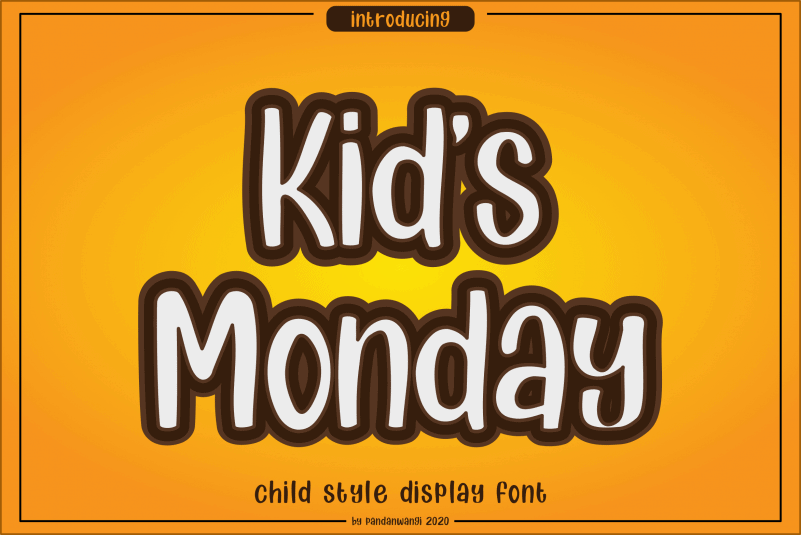
Kids Monday Display Font – Fonte Grátis
Kids Monday Display Font
A Kids Monday Display Font é uma escolha perfeita para aqueles que buscam um toque divertido e criativo para seus projetos digitais. Desenhada pelo designer pandanwangi, ela carrega um estilo natural e único, adequado para qualquer aplicação visual que exigir um touch de diversão. Seja o texto em uma camiseta personalizada ou a identidade de um canal do YouTube, ou até mesmo os rótulos dos seus produtos finais, essa fonte traz um brilho encantador e irreverente para todos eles. Com sua natureza amigável e divertida, Kids Monday Display Font é especialmente adequada para projetos que exigem uma pitada de fantasia. Ela é perfeita para criar slogans memoráveis ou designar canais de mídia social com personalidade. E mais do que isso, ela permite que seu imaginário se realize em qualquer design que você possa imaginar. Sua versatilidade e estilo único garantem que seja fácil encontrar uma maneira criativa de incorporá-la em projetos semelhantes a um tópico, uma marca ou até mesmo um banner de evento especial. Além disso, Kids Monday Display Font não se limita a espaços pequenos – sua natureza robusta e única permite que seja usada para textos em grandes dimensões como design de piscinas de grama e identidade visual de marcasres. E com apenas as possibilidades infinitas do seu próprio imaginário, o limite é realmente sua imaginação. Em um mundo cada vez mais digitalizado, a Kids Monday Display Font está aqui para tornar os seus projetos únicos e divertidos.